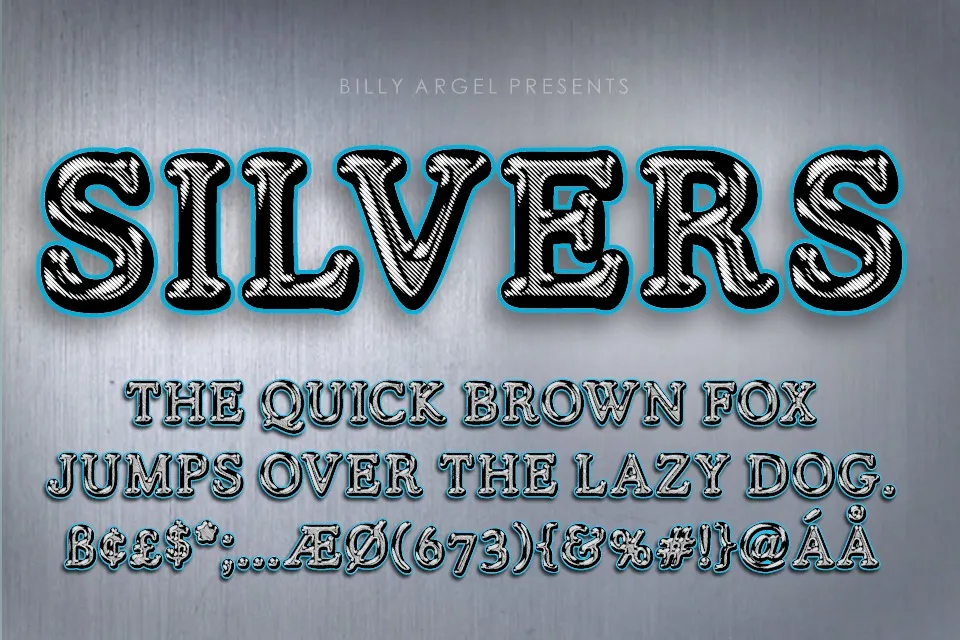
Silvers Font – Fonte Grátis
Silvers Font
A “Silvers Font” é uma fonte serif bold e condensada, criada pelo talentoso designer Billy Argel a partir do catálogo de 99designs. Esta font vintage destaca-se por sua simplicidade e elegância moderna, que se adaptam perfeitamente para diversas aplicações gráficas. Perfeita tanto para projetos de marca como para criações de móveis de casa ou embalagens de produtos, a “Silvers Font” também é uma escolha ideal para o design de cabeçalhos em revistas e simplesmente como overlay de texto estilizado para qualquer imagem de fundo. Esta font vintage não apenas mantém seu charme retrô mas também oferece um toque moderno que complementa perfeitamente projetos digitais contemporâneos, tornando-a uma opção atraente para designers buscando uma combinação única e única entre outras fontes disponíveis no mercado.